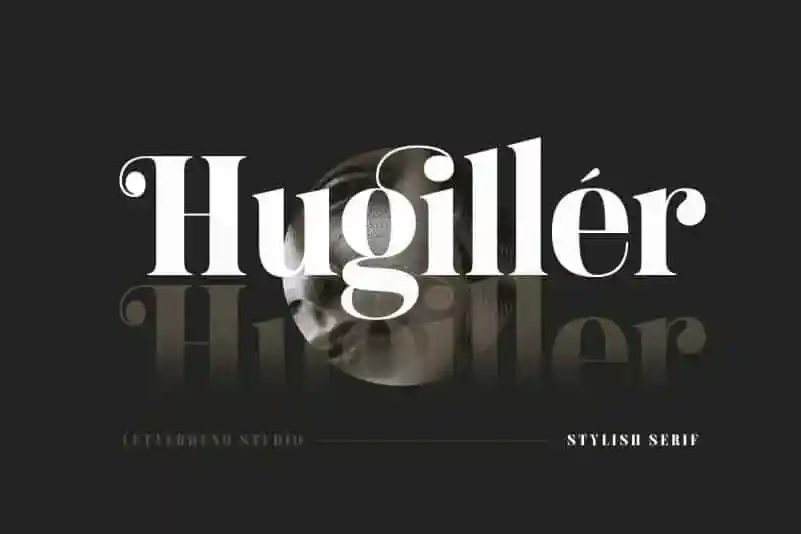
A Hugiller Serif Font é uma tipografia serifada condensada criada pela Letterhend Studio, com uma característica única que a faz ainda mais especial: os ligantes, pequenos conjuntos de letras ou símbolos que formam um único caractere mais complexo. Esta singularidade proporciona ao leitor uma sensação atemporal e sofisticada simultaneamente, trazendo um toque moderno ao mesmo tempo nostálgico. Confeccionado para o uso em logotipos e outros formatos formais como convites, rótulos, selos, revistas, livros, cartas de cumprimento ou casamento, embalagens, moda, maquiagem, estaçãoaria e literatura, a Hugiller Serif Font promete dar um toque único e sofisticado para qualquer tipo de fim publicitário. Não importa qual seja o seu projeto, este font pode ajudar você a torná-lo ainda mais profissional e memorável.